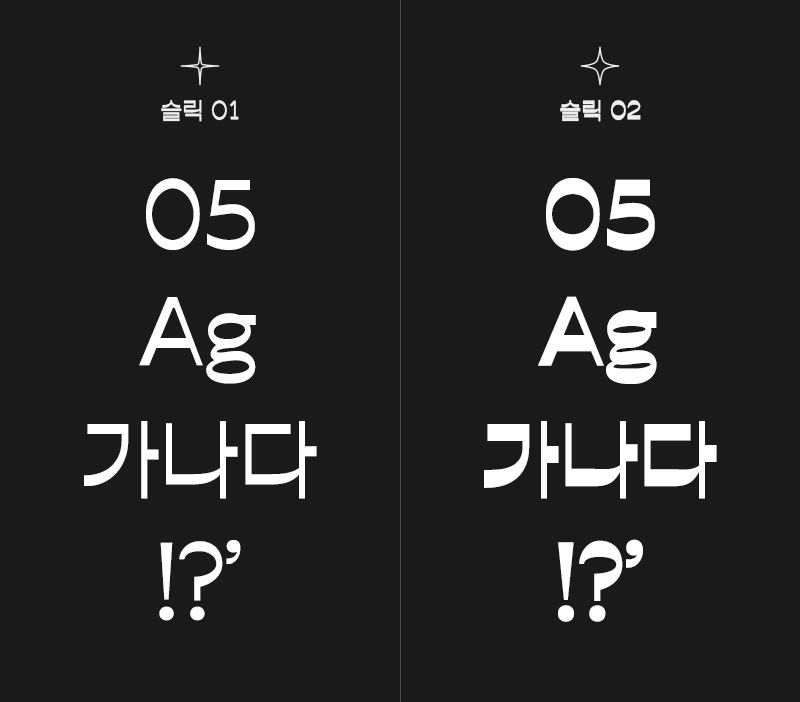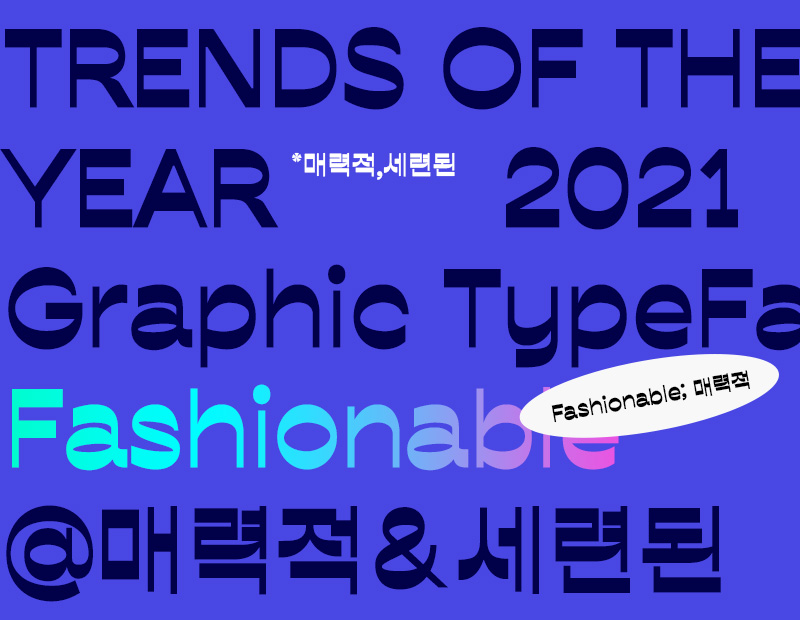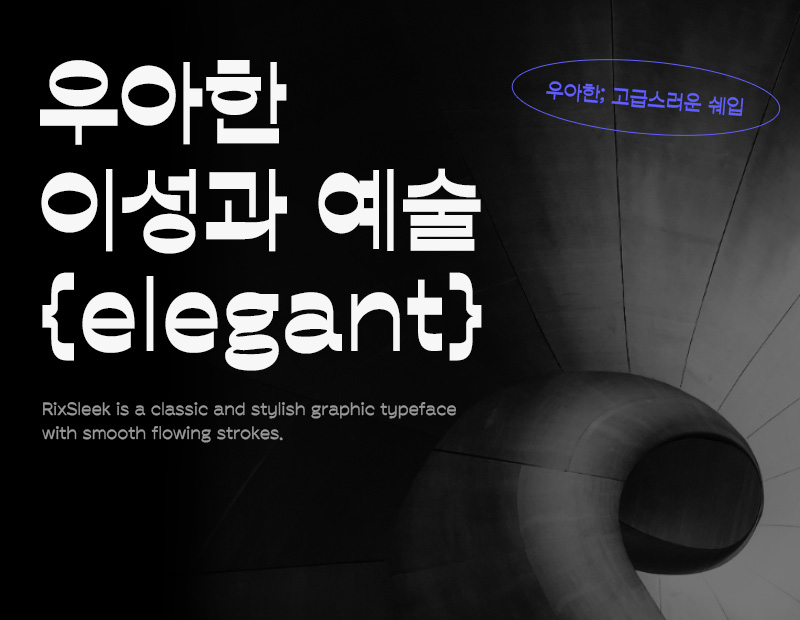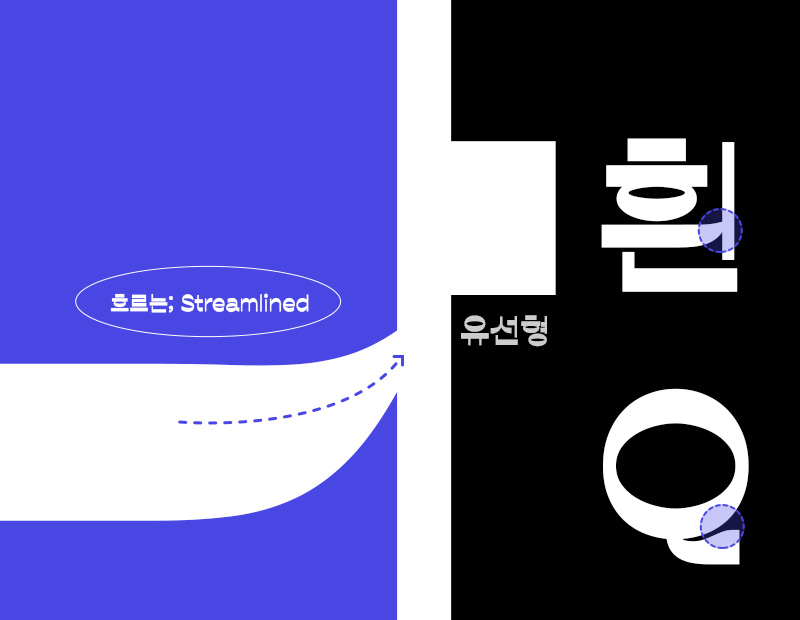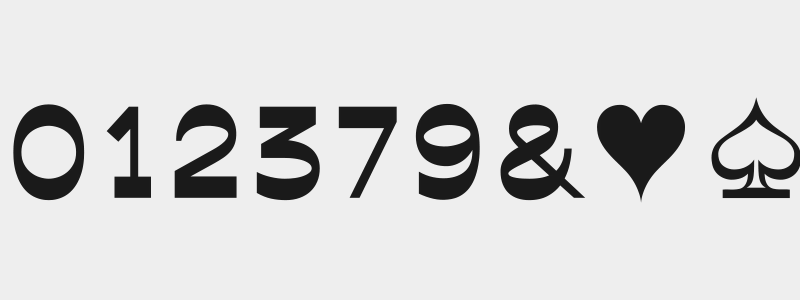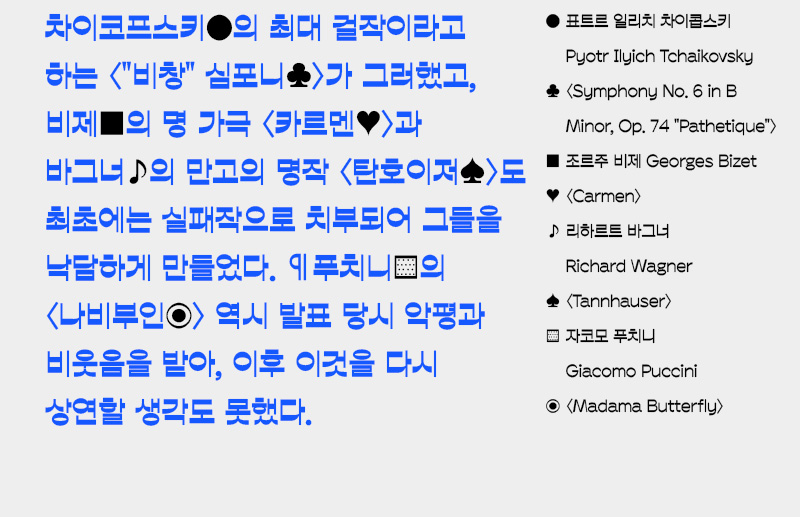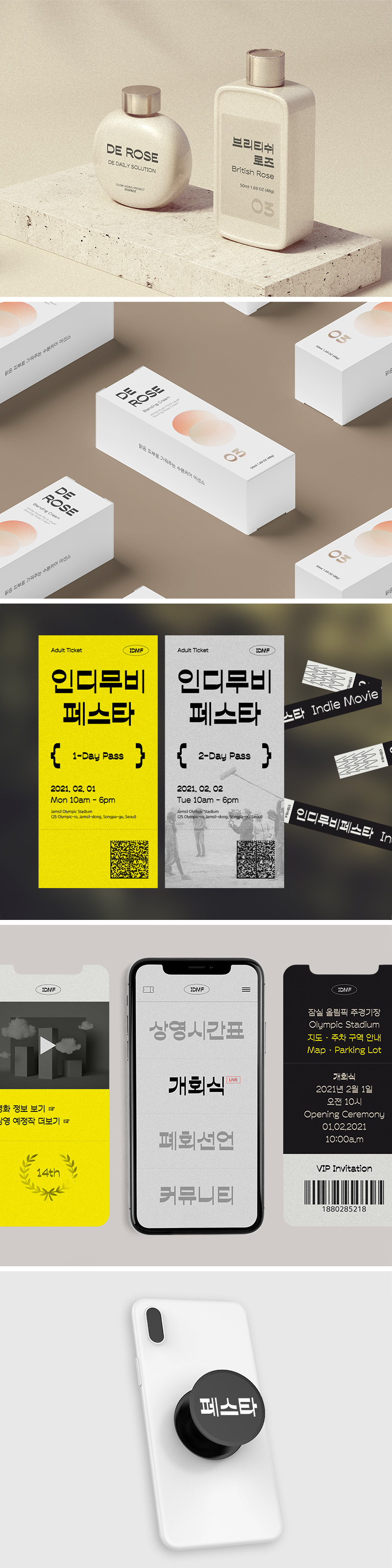
Rix슬릭
2 종 - 02, 01Rix슬릭은 매끄럽게 흐르는 획을 가진 클래식하고 세련된 그래픽 서체입니다.
감각적인 쉐입은 패셔너블한 인상을 주며 영문에도 동일한 느낌을 주었습니다.
| 폰트명 | Rix슬릭 / RixSleek |
| 폰트디자인 | 조소희 |
| 디자인디렉팅 | 박용락 |
| 출시년도 | 2021년 |